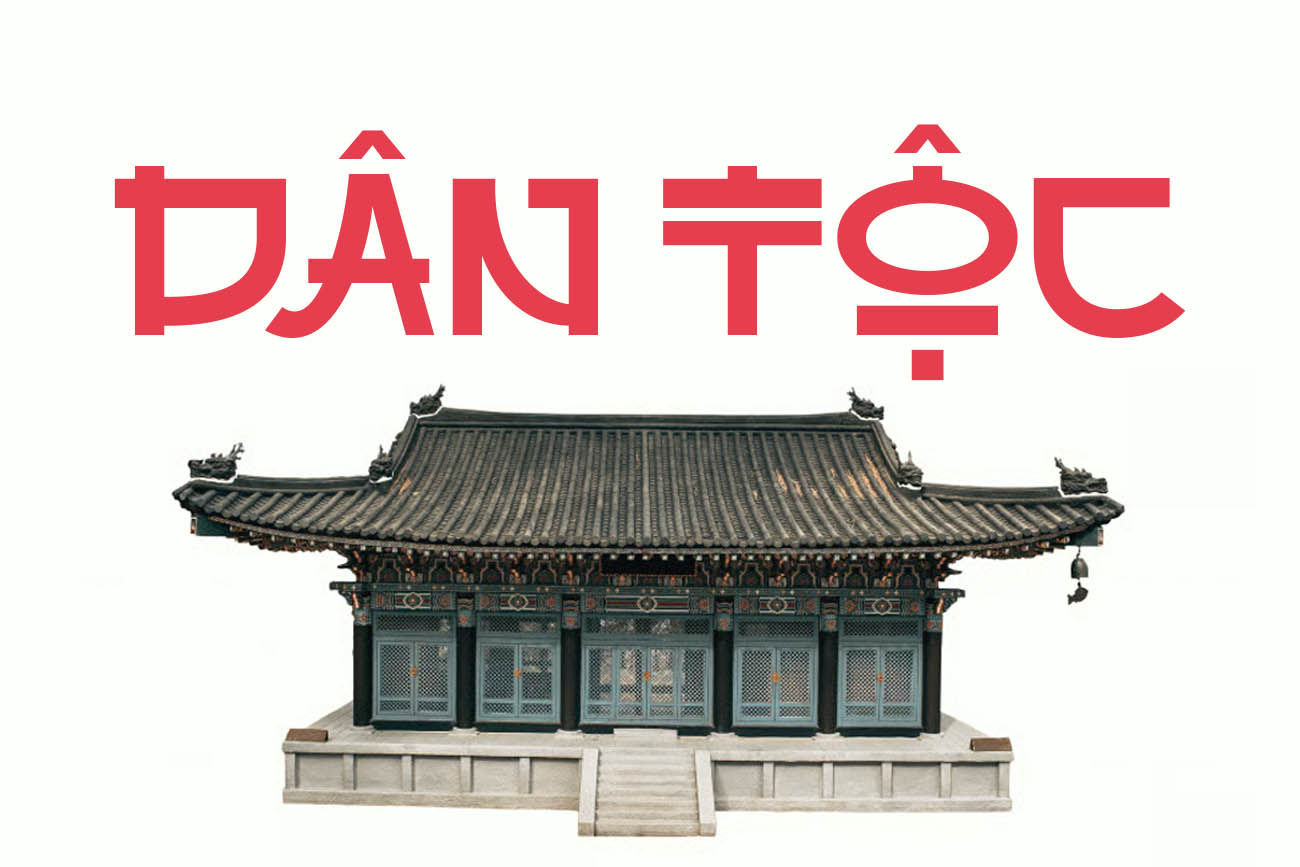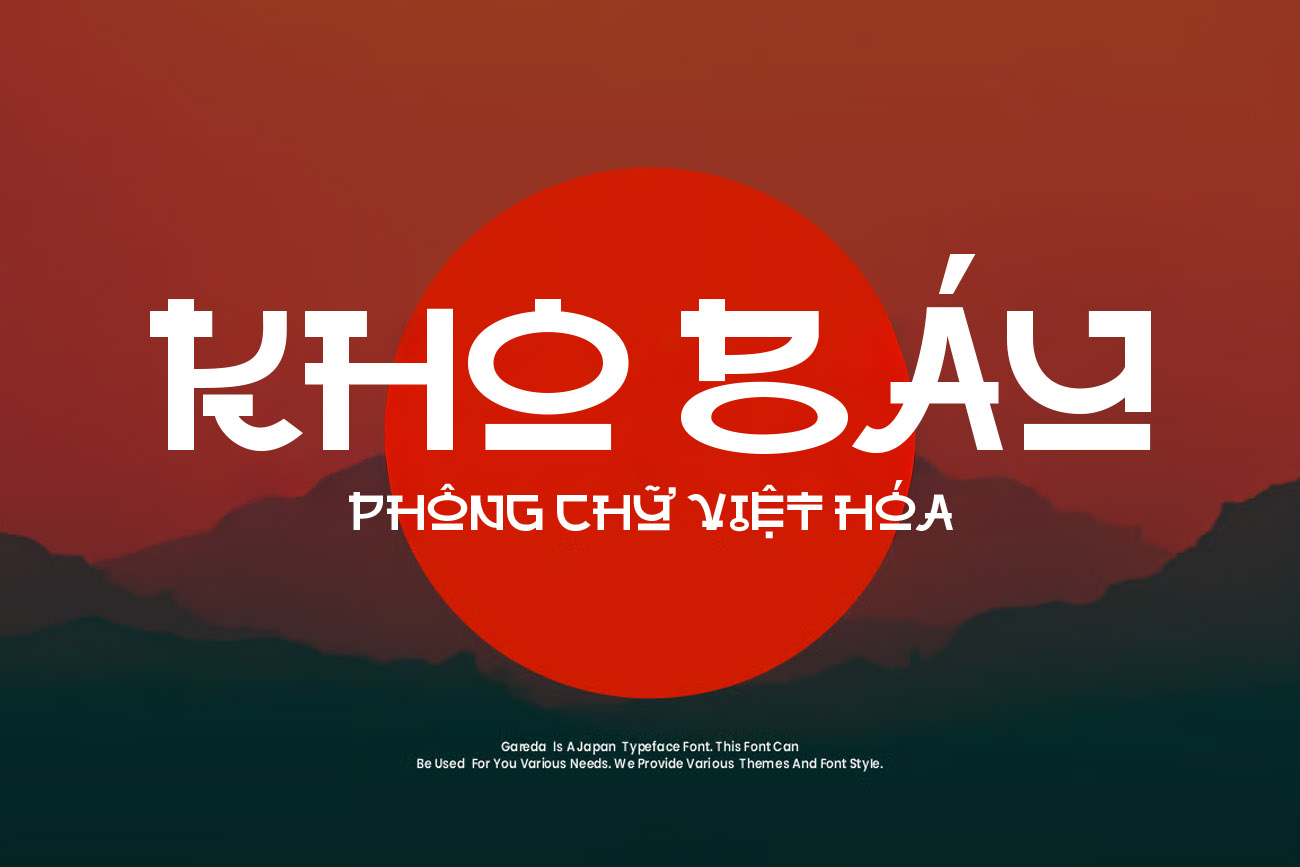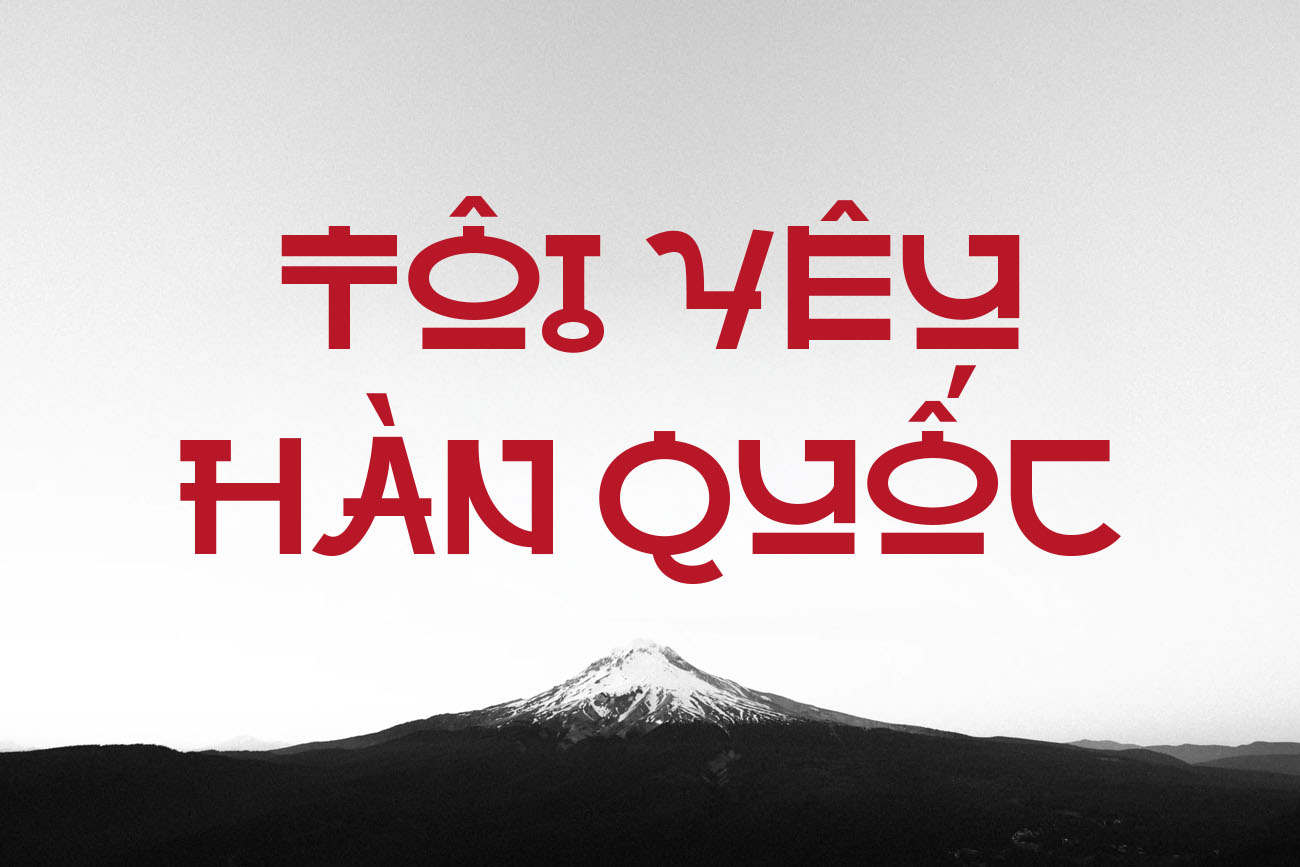
Font chữ Hàn Quốc độc đáo cho thiết kế TH Raboan Việt hóa
Trong xu hướng thiết kế đồ họa hiện đại, việc ứng dụng các nét văn hóa Á Đông vào typography đang trở thành một làn gió mới đầy sức hút. Nếu bạn đang tìm kiếm sự phá cách để tạo điểm nhấn cho các dự án sáng tạo của mình, phiên bản font chữ việt hóa TH Raboan chính là lựa chọn không thể bỏ qua. Đây là sự kết hợp hoàn hảo giữa cấu trúc Latin và tinh thần thẩm mỹ xứ sở Kim Chi.
Font chữ Hàn Quốc độc đáo cho thiết kế TH Raboan Việt hóa
Vẻ đẹp độc bản của Raboan – Khi Latin mang hồn Á Đông
Raboan là một tác phẩm typography ấn tượng được sáng tạo bởi twinstd. Điểm đặc biệt nhất của bộ phông này nằm ở phong cách giả lập chữ Hangul (Hàn Quốc). Tác giả đã khéo léo vay mượn các nét cọ, hình khối tròn và vuông đặc trưng trong bảng chữ cái tiếng Hàn để tái cấu trúc lại các ký tự Latin.
Chính nhờ tư duy thiết kế này, Raboan mang đến một font chữ hàn quốc (Korean style font) cực kỳ thuyết phục về mặt thị giác mà vẫn đảm bảo người xem có thể đọc hiểu nội dung tiếng Anh hoặc tiếng Việt một cách dễ dàng. Font chữ này cực kỳ phù hợp cho các thiết kế Poster, bìa tạp chí, logo thương hiệu, bao bì sản phẩm hoặc các tiêu đề cần sự ấn tượng mạnh mẽ.
Font chữ Hàn Quốc độc đáo cho thiết kế TH Raboan Việt hóa
Tại sao nên sử dụng phiên bản Việt hóa TH Raboan?
Mặc dù bản gốc từ twinstd rất đẹp, nhưng rào cản lớn nhất đối với các Designer Việt Nam chính là hệ thống dấu câu. Việc sử dụng font gốc thường dẫn đến lỗi hiển thị khi gõ tiếng Việt, làm mất đi tính thẩm mỹ và sự chuyên nghiệp của bản thiết kế.
Hiểu được nhu cầu đó, đội ngũ TH đã thực hiện Việt hóa bộ phông này với tên gọi TH Raboan. Phiên bản này không chỉ đơn thuần là thêm dấu, mà các dấu câu được tinh chỉnh kỹ lưỡng về vị trí (kerning) và độ dày để hòa hợp hoàn toàn với tổng thể nét vẽ "giả Hàn" của font gốc.
Font chữ Hàn Quốc độc đáo cho thiết kế TH Raboan Việt hóa
Lời kết